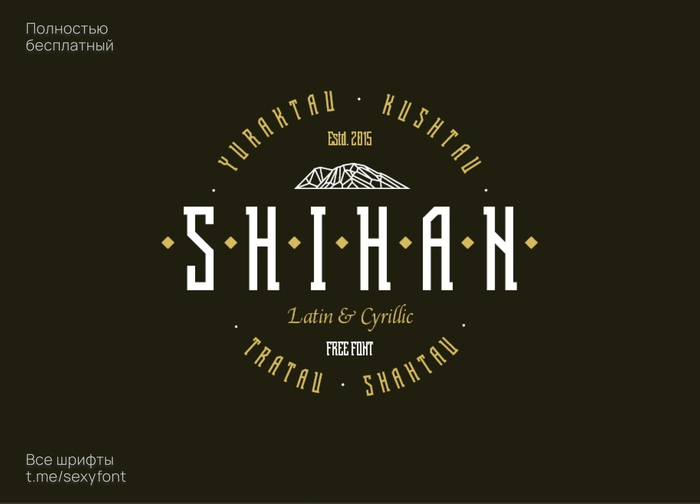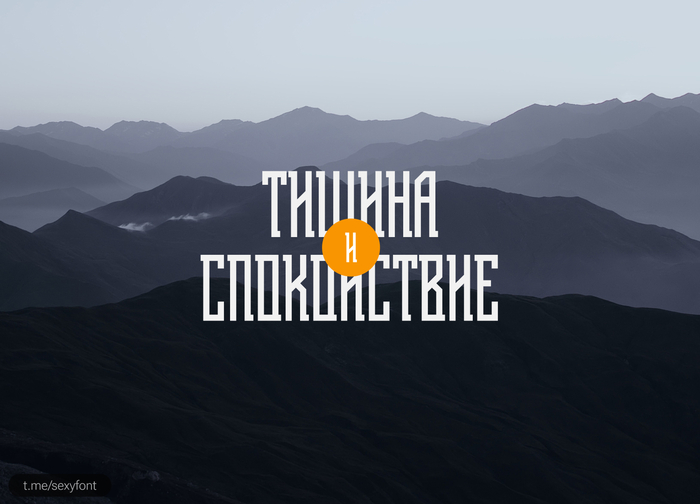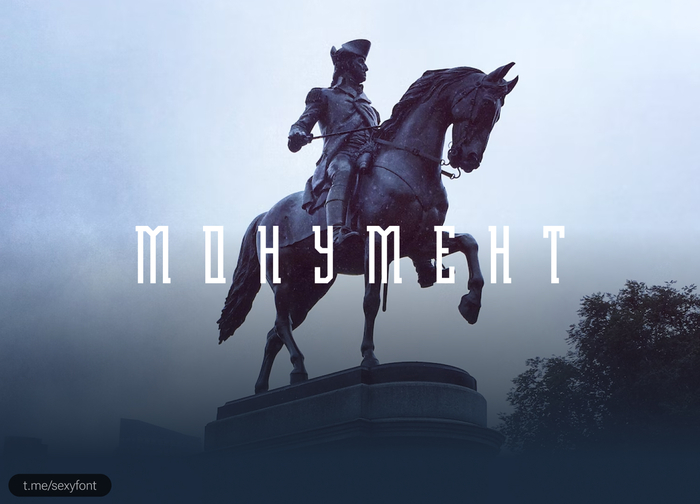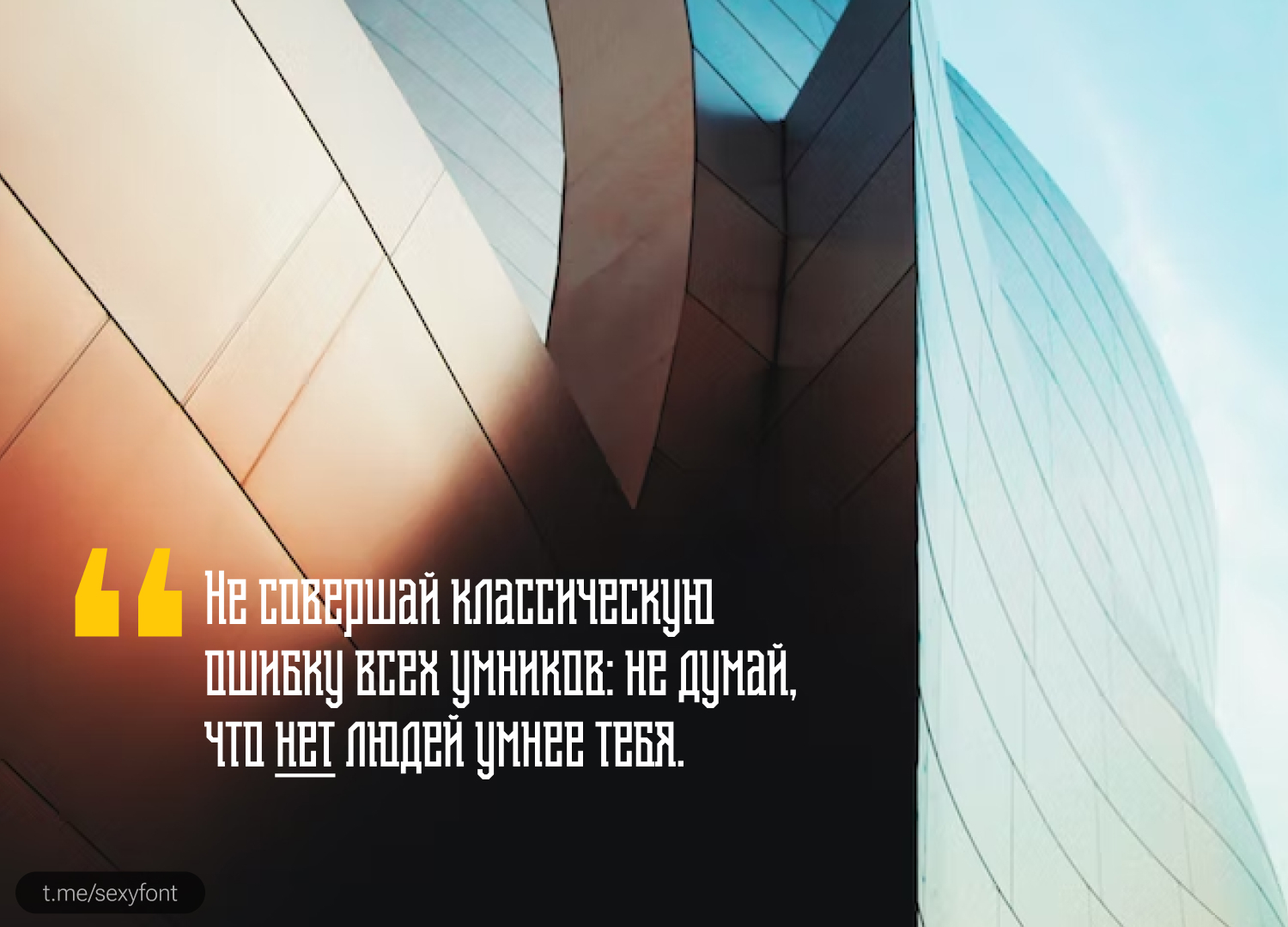
Бесплатный шрифт шихан. Кириллица
Шрифт Шихан. Назван в честь горы, на которой я был кстати)
От автора: Бесплатный шрифт, вдохновленный башкирскими геометрическими орнаментами. Это БЕСПЛАТНЫЙ шрифт, и его разрешено использовать в коммерческих целях. Шихан поставляется в формате OpenType и поддерживает базовую латиницу, кириллицу и башкирский язык. Это акцидентный шрифт, для сохранения читаемости лучше использовать в коротких заголовках. Автор: Sergei Godovalov